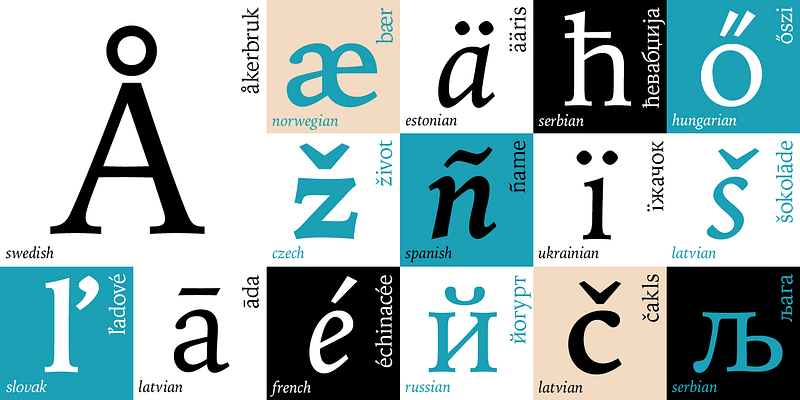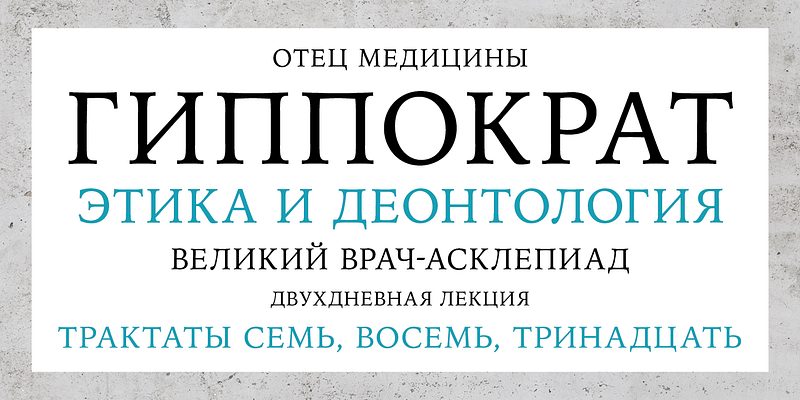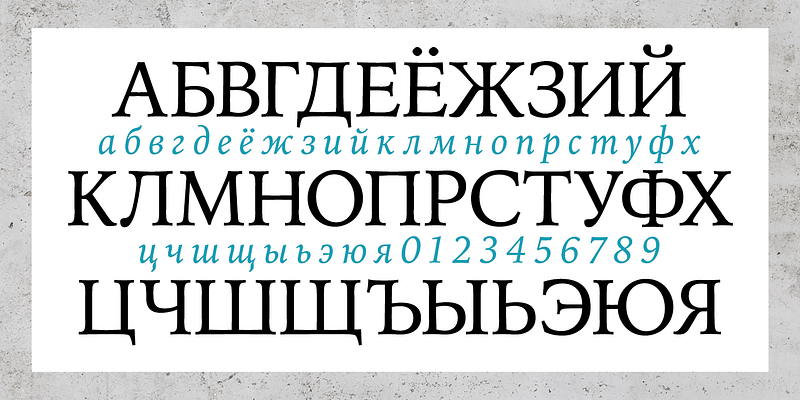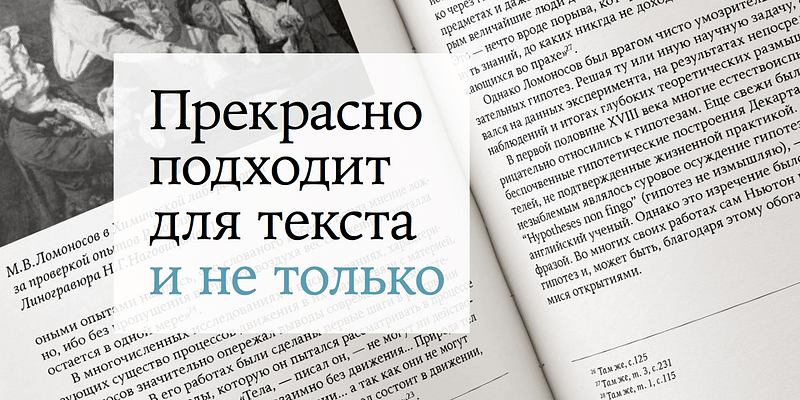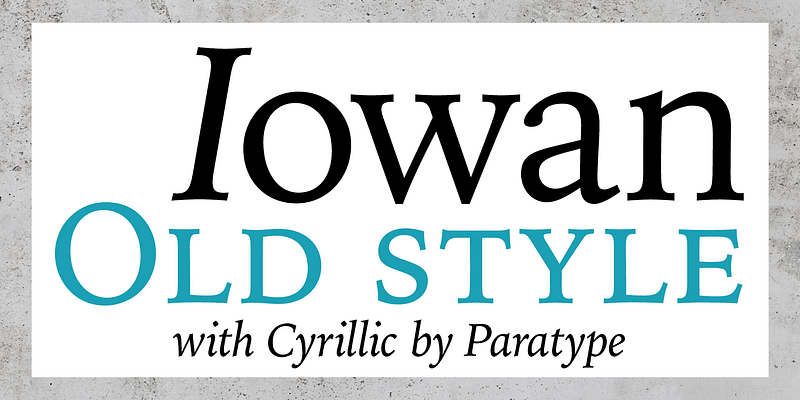
Iowan Old Style wurde 1990 vom bekannten Schildermaler John Downer für Bitstream entworfen. Iowan Old Style ist ein robustes, modernes Text-Design, das sich an früheren Neuauflagen der Jenson- und Griffo-Schriften orientiert, jedoch eine größere x-Höhe, einen engeren Buchstabenschnitt und neu proportionierte Großbuchstaben aufweist. Die kyrillischen Buchstaben wurden 2016 von Natalia Vasilyeva entworfen. Iowan Old Style Cyrillic wurde 2017 von Paratype veröffentlicht.